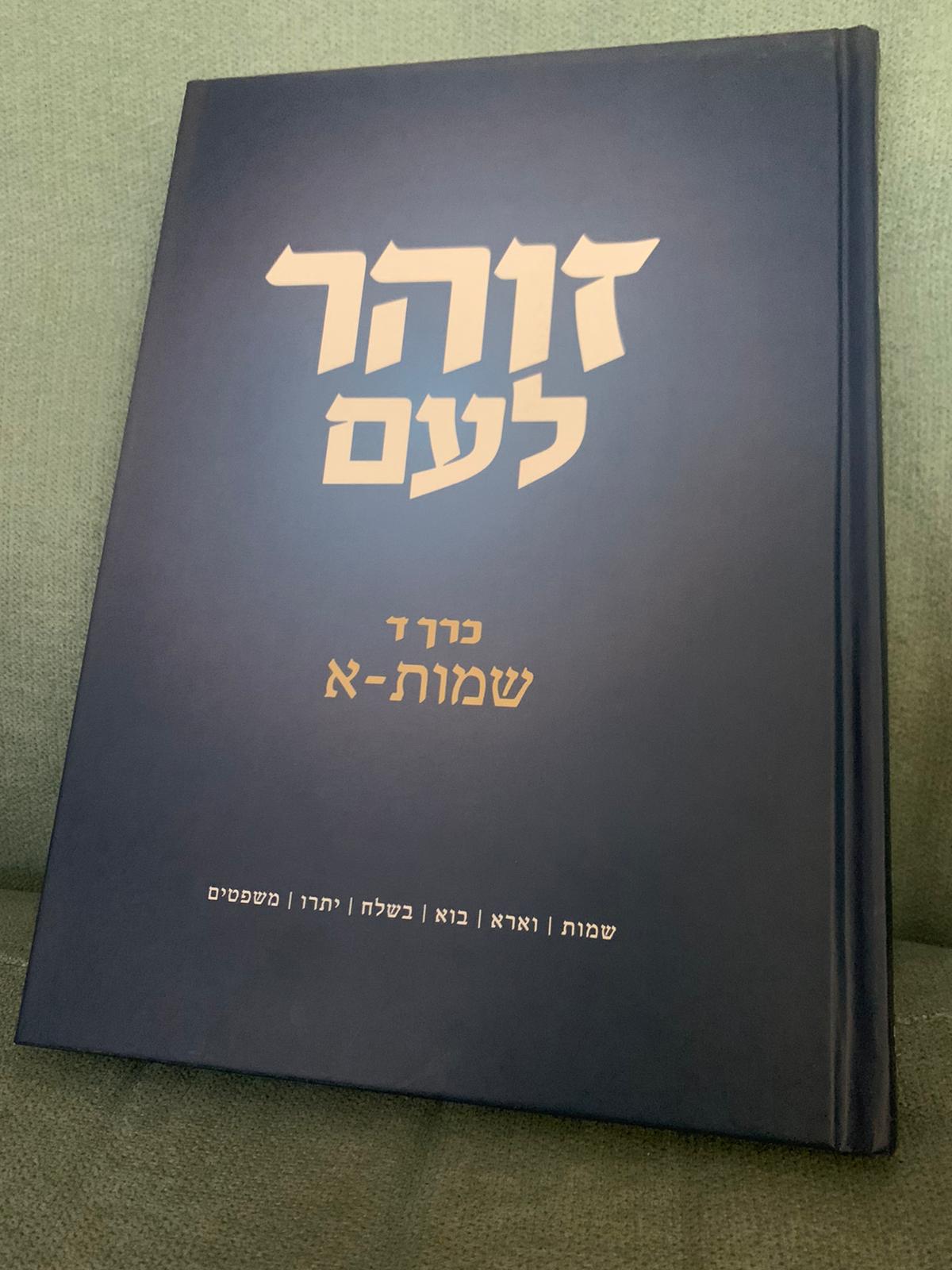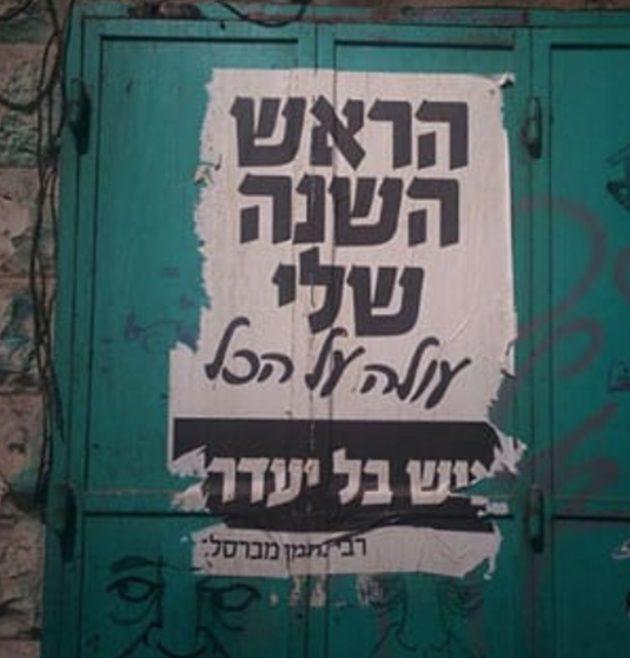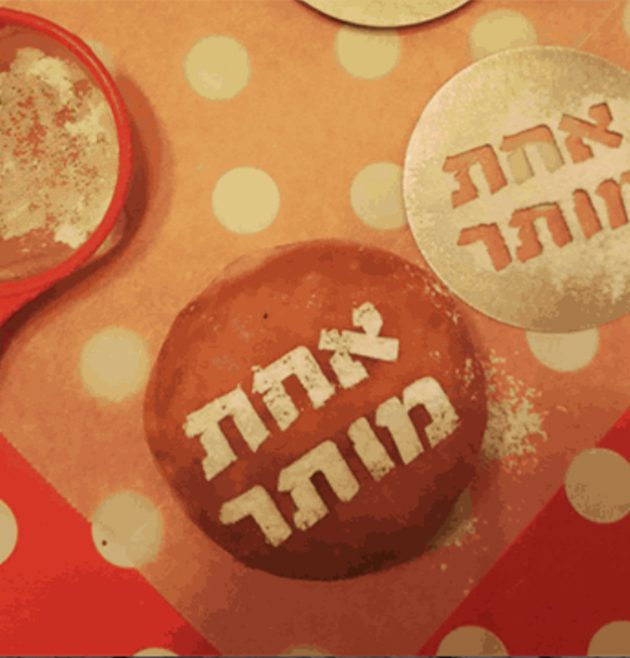
סנדלר
סנדלר / Sandlar
• שם הגופן:סנדלר
• מעצב הגופן:נדב עזרא
• סגנון:סלאב סריף
• קטגוריה: עברית טקסט ראווה
• מאפיינים: רגיל כבד שחור
• תכונות: הומניסטי מהודר מרובע נוסטלגי קלאסי קשיח רוחני
סיפור הגופן:
גופן המתאים לגושי טקסט קצרים ולא לקריאה ממושכת. אות זו מתאימה למיתוג או לעימוד של טקסט קצר כדוגמת קטלוגים. יתרונה של האות הוא בכך שאינה מתעייפת מהר כמו אות ראווה. כלומר, עיצוב האות אינו נישתי או מפורש וגרפי כמו "אות ראווה", אלא שומר על קריאות, הרמוניה, ועניין גרפי, מה שמאפשר לגופן לשמש למגוון שימושים. ברוב המקרים מדובר ב"משפחות גופנים" בעלי משקלים מרובים, מה שפותר טווח אפשרויות גיוון בעימוד, מבלי שיאבד אותו ניחוח ייחודי של טיפוס האות. גופנים מסוג זה הם לעתים קרובות גופנים נטולי עוקצים בדומה לאותיות ה"סנס-סריפיות" הלועזיות, ולעתים קרובות בעלי צורה נקייה ומדויקת אף על פי שאין הדבר מחייב.